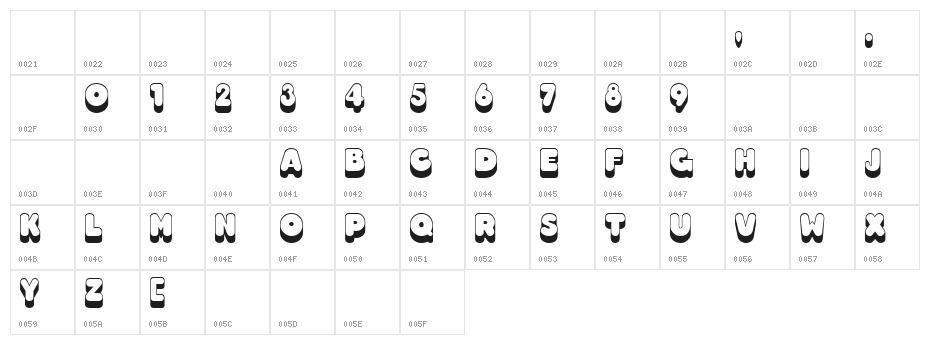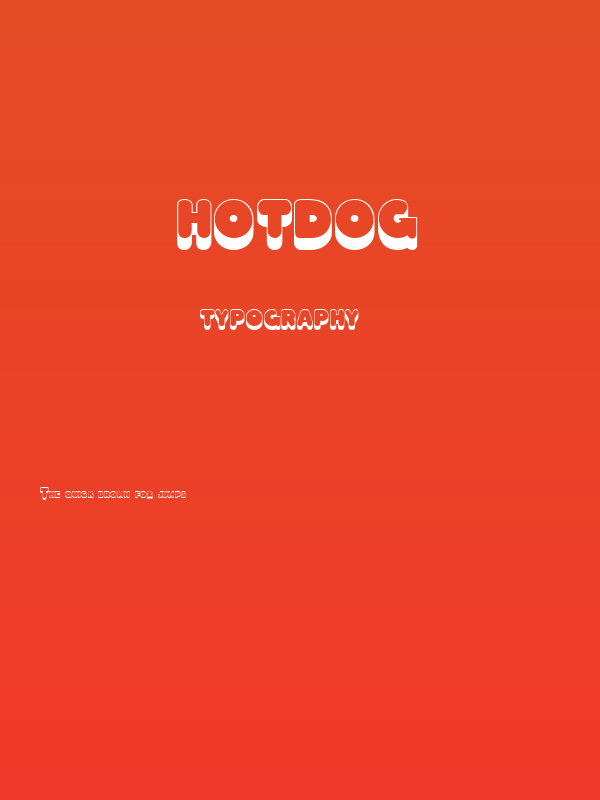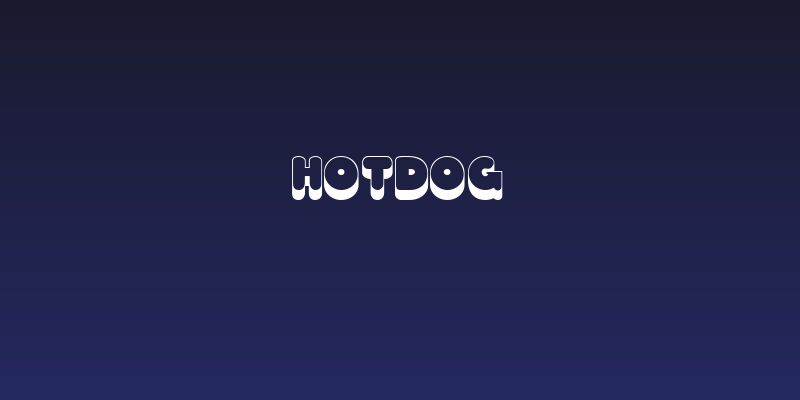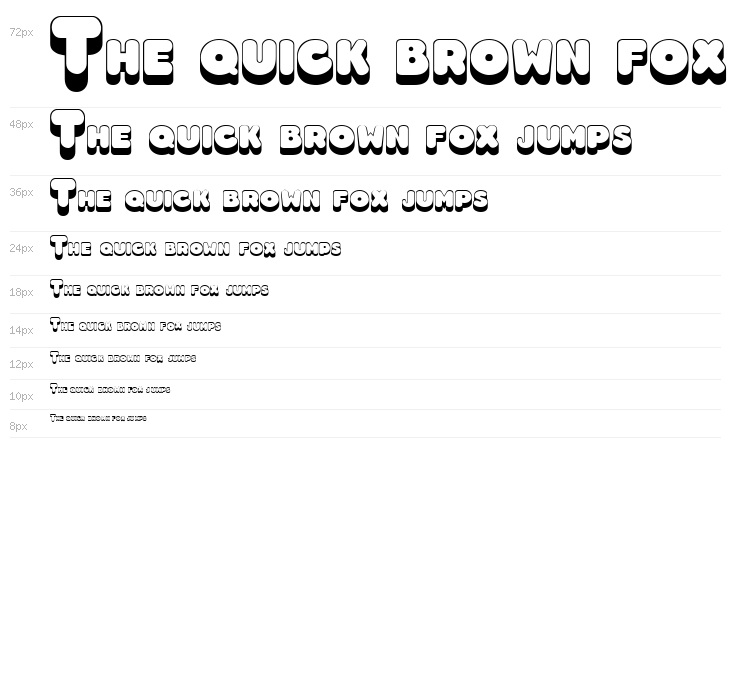
HotDog Font
| Gesamtstil | Playful, Retro |
| Vorgeschlagene Projekte | Ideal for children's book covers, comic strips, playful branding, party invitations, and eye-catching posters. |